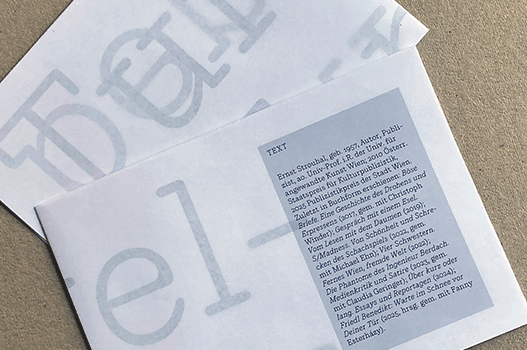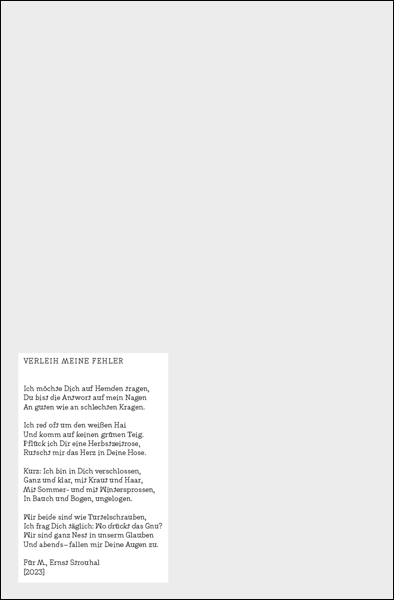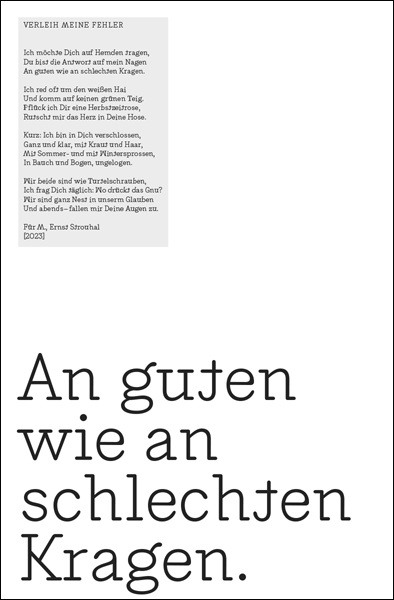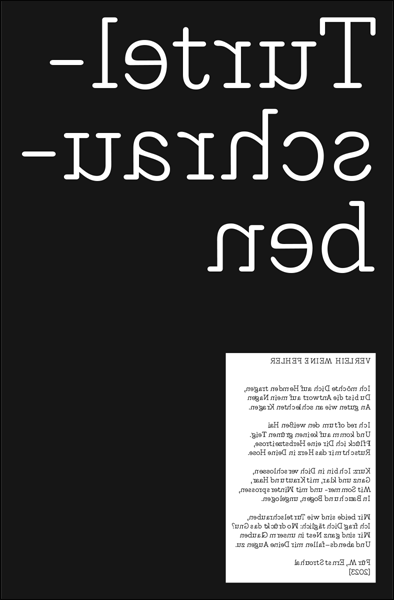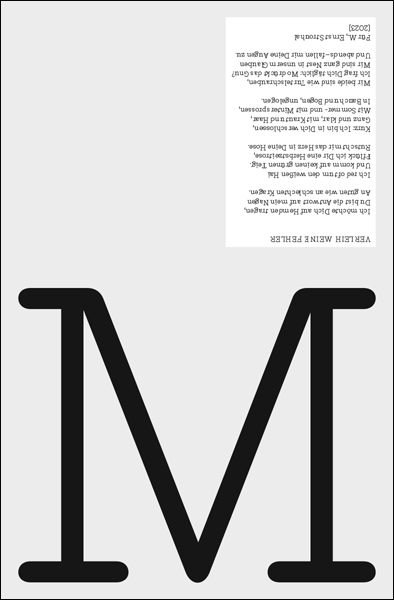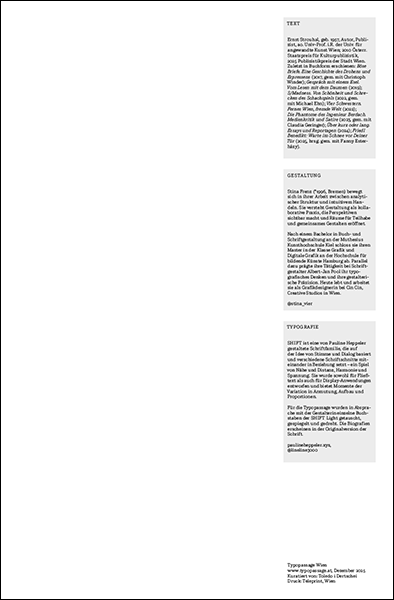
Typografie
SHIFT ist eine von Pauline Heppeler gestaltete Schriftfamilie, die auf der Idee von Stimme und Dialog basiert und verschiedene Schriftschnitte miteinander in Beziehung setzt – ein Spiel von Nähe und Distanz, Harmonie und Spannung. Sie wurde sowohl für Fließtext als auch für Display-Anwendungen entworfen und bietet Momente der Variation in Anmutung, Aufbau und Proportionen.
Für die Typopassage wurden in Absprache mit der Gestalterin einzelne Buchstaben der SHIFT Light getauscht, gespiegelt und gedreht. Die Biografien erscheinen in der Originalversion der Schrift.